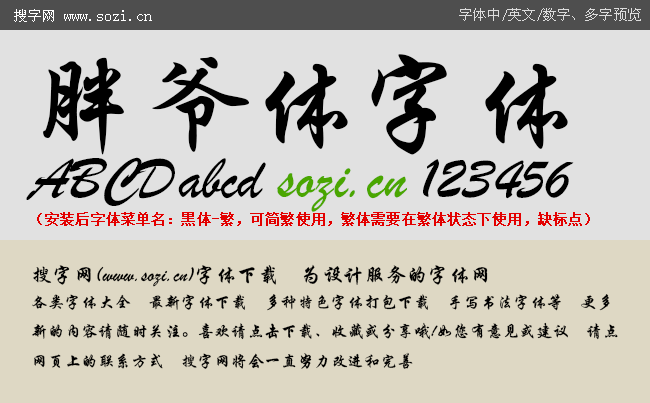
胖爺體字體
搜字網(wǎng)給大家提供一款胖爺體字體手機(jī)中文字體下載。這款手機(jī)字體是一款行楷字體,行楷的用筆靈活、方便,筆道流暢,使轉(zhuǎn)合理,行筆巧妙,靈活多變,特別適合喜歡手機(jī)字體個(gè)性一些的朋友在手機(jī)上安裝使用。
• 風(fēng)格類別: 行楷